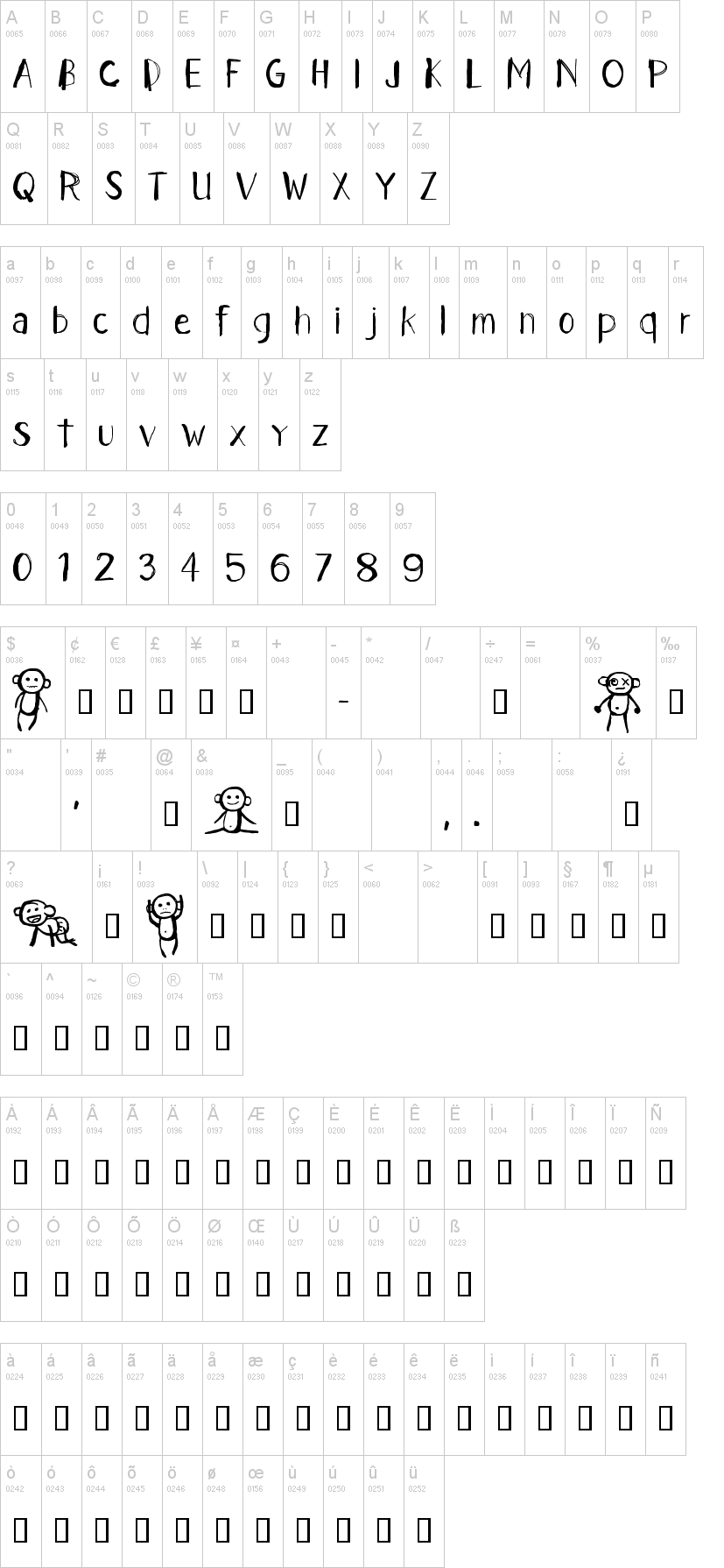
CF I Dont Want to Grow Up
CF I Don’t Want to Grow Up 是一款由 Creative Fonts 出品的手写体字体。它采用简洁而又充满活力的设计,令人印象深刻。它以独特的手写体风格呈现文字,使文字具有活力和温暖的感觉。这款字体的特点是:它的字母和数字具有活力和温暖的感觉,有助于提升文字的表现力;它的笔画细腻流畅,使文字看起来更加有趣;它的字体结构紧凑,可以使文字看起来更加美观;它的字体重量轻,可以使文字看起来更加清晰。CF I Don’t Want to Grow Up 字体适用于各种不同的设计项目,比如海报、书籍、网页等等。
CF I Dont Want to Grow Up是一款非常不错的手写艺术字体,具有很好的视觉感,适合于文化类的宣传设计、商业类品牌的广告和产品包装设计以及个性化文字排版等较多场景。